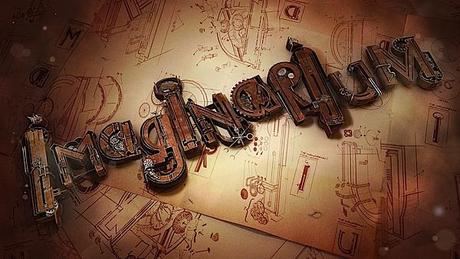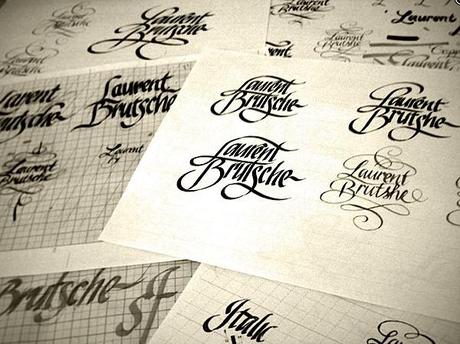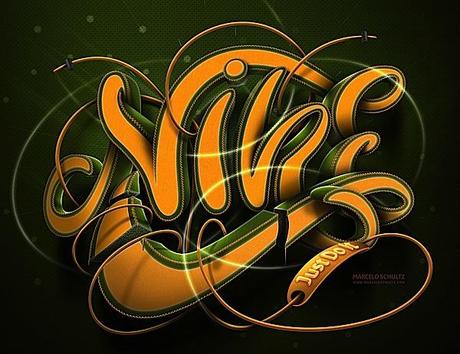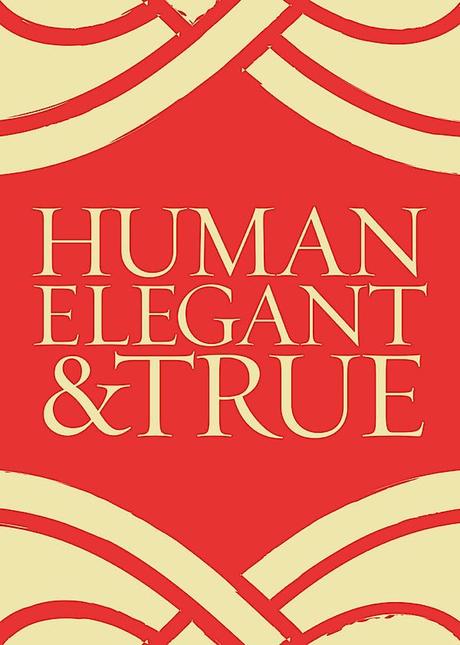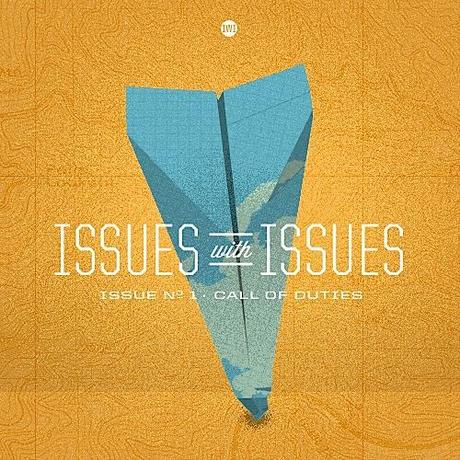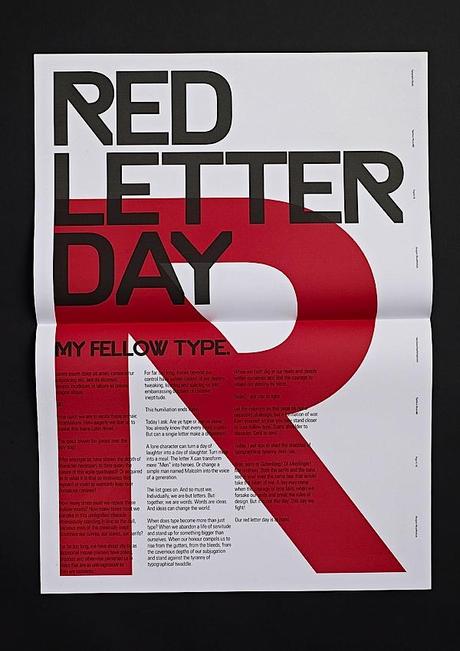
Tipografia creativa nel Web
Alla tipografia abbiamo dedicato molti articoli. Abbiamo presentato  alcuni esempi per capire l’importanza dell’uso dei font e come sia affascinante trasformare un semplice testo in un’illustrazione che comunica molto piu velocemente e in modo piu’ diretto il messaggio che vogliamo dare. In questo articolo proponiamo altri capolavori tipografici per meglio approfondire il concetto di tipografia. Insomma col font giusto ed elaborato a dovere si riesce a sviluppare delle illustrazioni uniche e dei disegni di alta qualita’ che riescono a colpire l’utente e a passargli il giusto messaggio.